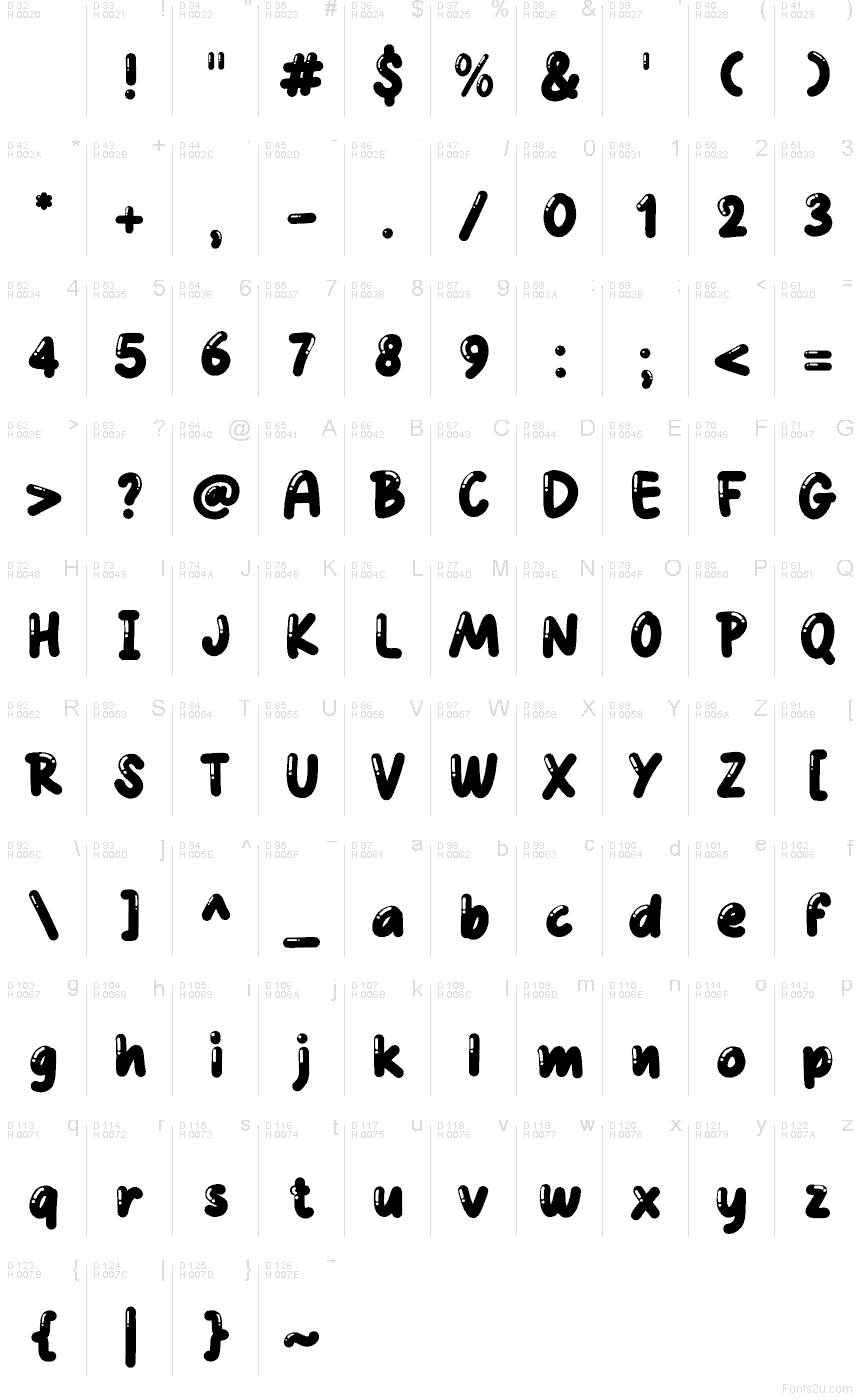
Jump Bubble
Jump Bubble, créée par Hello Good Studio, est une police d'affichage gratuite au style cartoon, dotée de formes de lettres arrondies et gonflées, ainsi que de courbes douces et inclinées. Le dessin semble fait à la main et dynamique, avec des coupes intérieures étroites et de petites ouvertures en forme de goutte d'eau qui confèrent à la typographie un caractère vivant, digne d'une bande dessinée.
Jump Bubble est parfaite pour l'image de marque destinée aux enfants, les invitations aux fêtes, les titres d'affiches, les logos, le packaging et les visuels pour réseaux sociaux, car ses formes arrondies sont à la fois amusantes et informelles sans pour autant perdre en lisibilité. Cette police gratuite est également idéale pour la création d'autocollants, de produits dérivés ludiques et d'accents sur les menus, lorsque vous souhaitez un style de titre à la fois pétillant et décontracté.